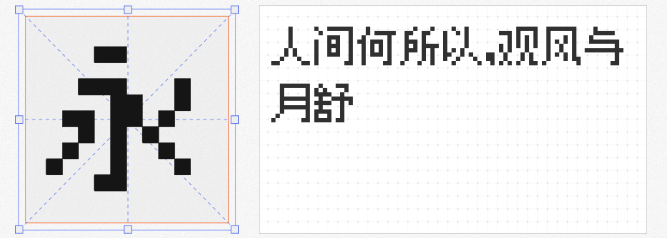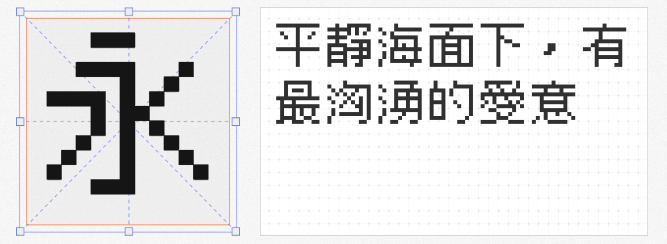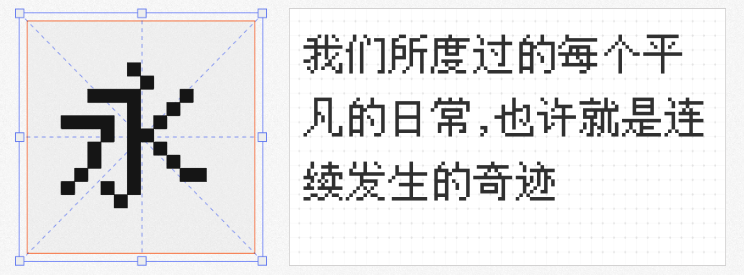
在像素风格回潮的当下,如何用字体为海报设计注入复古科技感?今天推荐四款免费商用像素字体,涵盖中文、日韩及多语言支持,适配游戏、科技、潮玩等多元场景,助你轻松打造记忆点。
作为自由中文字体中的"六边形战士",文泉驿点阵宋体以27842+汉字覆盖GB2312/Big5/GBK/GB18030标准,支持简繁中文、日韩文及多语言符号。其12px字号经过手工优化,21万汉字点阵在屏幕显示中锐利清晰,尤其适合需要密集文字排版的科技类海报。无论是复古游戏宣传图还是赛博朋克主题设计,这款开源字体都能兼顾可读性与风格化。
专为像素艺术游戏设计的LanaPixel以11px为基准,通过整数缩放(1x/2x/3x)保持像素完整性。其方块感字形与等宽结构完美适配8-bit风格海报,在复古游戏展、独立音乐节等场景中,能瞬间唤醒玩家对红白机时代的记忆。建议搭配低饱和度配色,强化怀旧氛围。
基于M⁺ gothic 12r衍生的俐方体11号,以开源姿态提供繁体中文点阵解决方案。其方正字形与像素块衔接自然,在港台风格茶饮品牌、复古电竞海报中表现突出。尤其适合需要体现"手作感"的场景,搭配故障艺术特效可增强视觉冲击力。
作为7px级小字号佼佼者,甜橙点阵体通过修正字高与ROS信息,解决了同类字体易模糊的痛点。其紧凑结构在软件界面、手游海报中能高效传递信息,同时保持像素风格的纯粹性。推荐用于需要突出数字/符号的科技类海报,如产品功能图解、数据可视化设计。